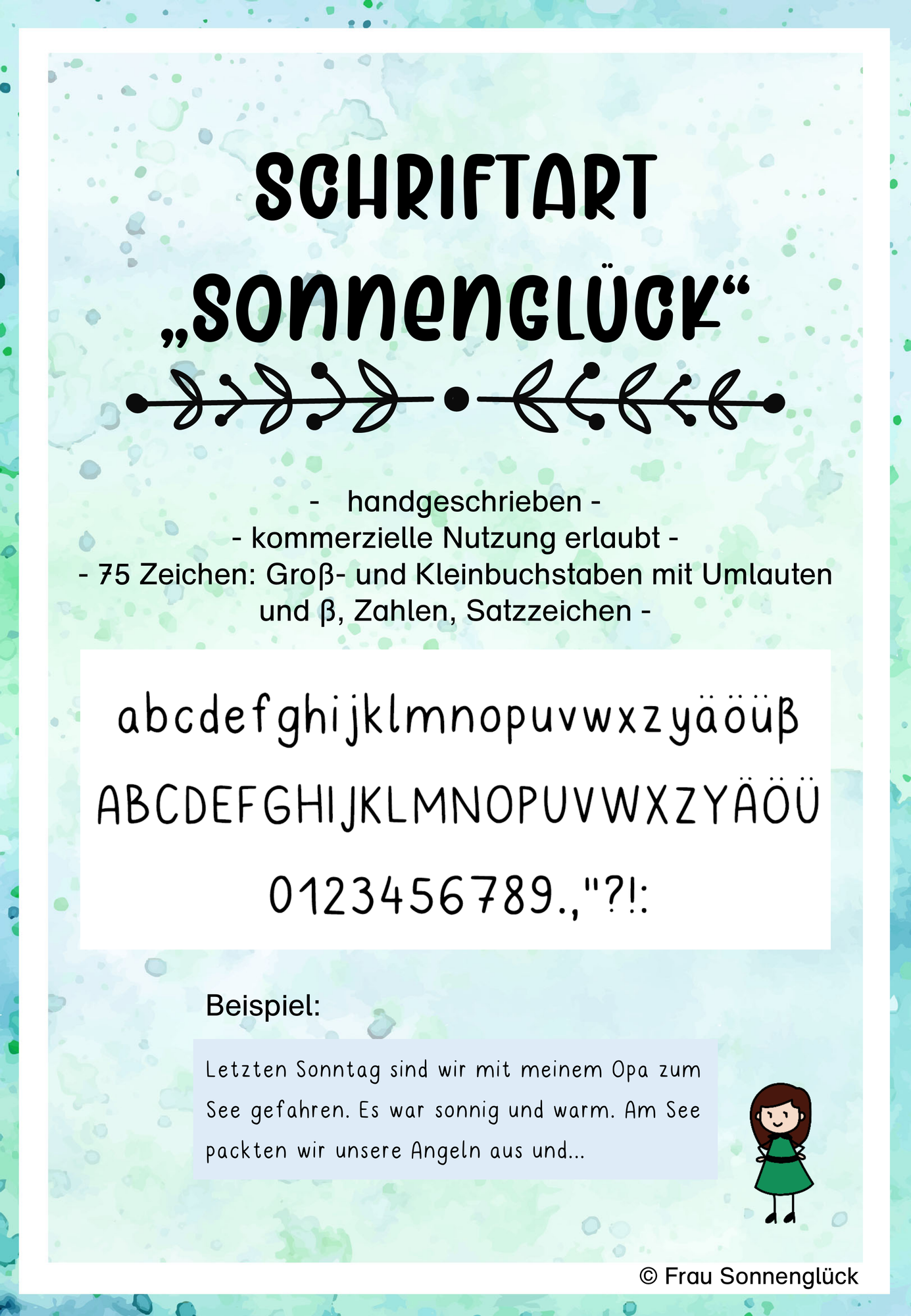
selbst erstellte Schriftarten - Schriftart "Sonnenglück" - 75 Zeichen - Frau Sonnenglück - Deckblatt
Das ist meine erste Schriftart, die sich aus meiner Handschrift ableitet. Sie besteht aus 75 Zeichen: Groß- und Kleinbuchstaben inkl. Umlaute und ß, alle Ziffern und die wichtigsten Satzzeichen (Punkt, Doppelpunkt, Komma, Ausrufe- und Fragezeichen, Anführungszeichen oben).
Schriftart "Sonnenglück" - 75 Zeichen